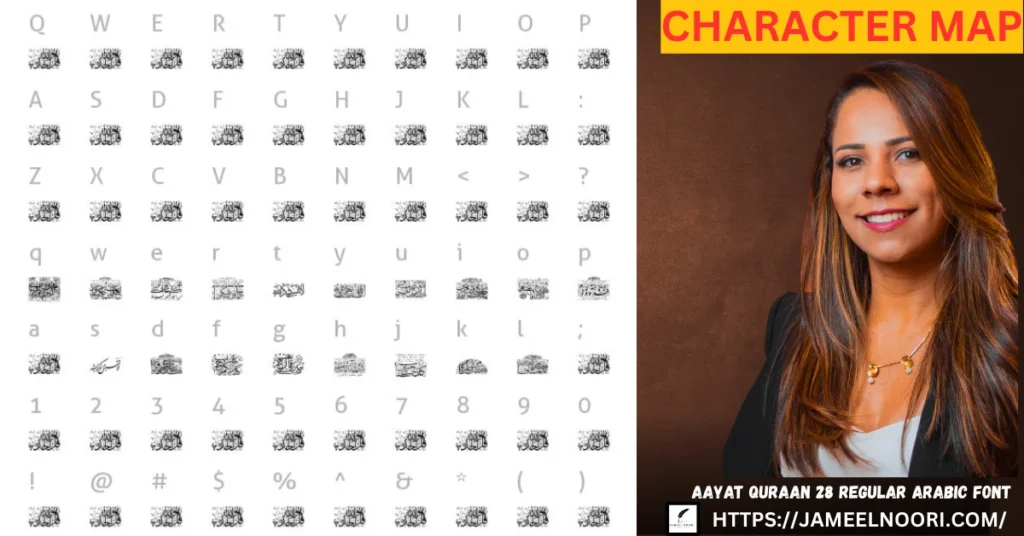
Introduction – Aayat Quraan 28 Regular Arabic Font Ko Pehle Jaaniye
Aayat Quraan 28 Regular Arabic Font aik bohot hi mashhoor aur widely used Arabic font hai jo Quranic ayat likhne, Islamic posters design karne aur Urdu Islamic content banane ke liye best samjha jata hai.
Ye font Pakistan, Lahore, Karachi, Islamabad aur India me bohot zyada popular hai kyunke iski readability aur calligraphy ka style bohot khubsurat lagta hai.
Font Background – History of Aayat Quraan 28 Regular
Aayat Quraan 28 Regular Arabic Font Aayat Quraan font family ka ek important member hai. Yeh family specifically Quranic text aur Islamic calligraphy ke liye design ki gayi thi.
Is font ko designers ne is liye banaya kyunke traditional Quranic fonts mein readability ka issue tha. Aayat Quraan 28 mein smooth character shapes aur balanced spacing di gayi hai jo Quranic text ko easily readable banati hai.
Aayat Quraan series ke fonts (10 se 56 tak) dhire dhire popular hue kyunke har version mein readability aur calligraphy style improve ki gayi. Aayat Quraan 28 un versions mein se ek hai jo balance aur clarity dono provide karta hai.
Font Preview – Design and Style
Aayat Quraan 28 Regular Arabic Font ki design bohot refined hai. Har letter ki shape smooth hai aur spacing balanced hai.
Font Preview Highlights:
- High-quality Quranic calligraphy
- Smooth character shapes
- No distortion in calligraphy
- Clear even at small sizes
- Professional appearance for Islamic designs
Key Features of Aayat Quraan 28 Regular Arabic Font
Aayat Quraan 28 Regular Arabic Font ke kuch popular features ye hain:
- Arabic aur Urdu Islamic content ke liye best readability
- High-quality Quranic calligraphy
- Print media, posters aur Islamic banners ke liye ideal
Font Comparison – Aayat Quraan 28 vs Other Arabic Fonts
Analysis: Agar aapko Quranic text aur Islamic designs me professional quality chahiye to Aayat Quraan 28 Regular Arabic Font sabse best choice hai.